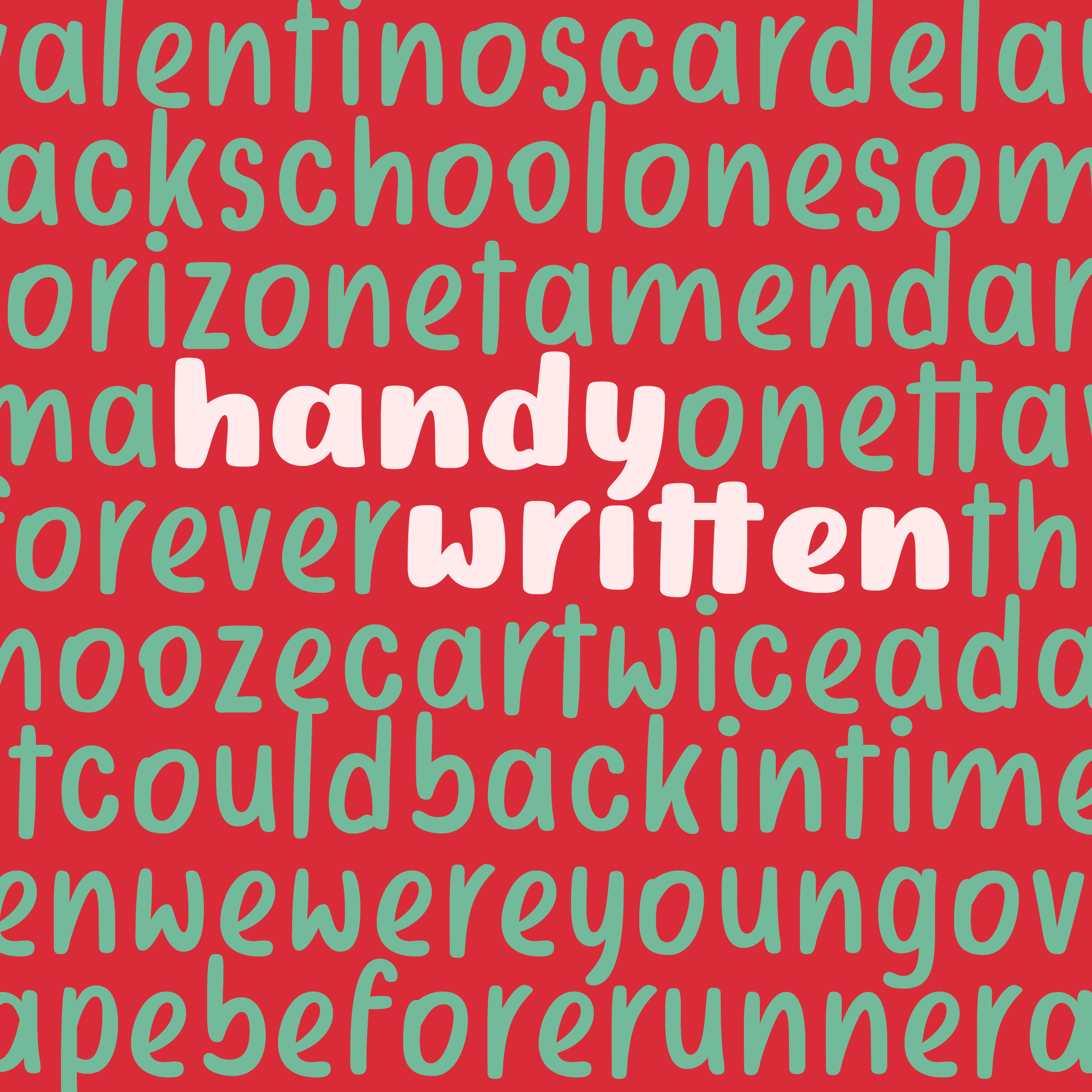
แฮนดี้ริทเทิ่น | HANDYWRITTEN
REMAKE PROJECT II
รีเมคใหม่หมด
ภาคต่อของฟอนต์ handywrite
ใช้วิธีทำงานแบบเดิม
เริ่มงานด้วย wacom แล้วค่อยมาแต่งหน้าทาปากเพิ่มหน่อยนึง
บุคลิกจะไม่ได้อิสระเสรีมากมายเหมือนแฮนดี้ไรท์
ชื่อฟอนต์ : แฮนดี้ริทเทิ่น | HANDYWRITTEN
แฮนดี้ริทเทิ่น | HANDYWRITTEN
REMAKE PROJECT II จากฟอนต์สุดฮิต ฟอนต์ "แฮนดี้ไรท์"
พัฒนาขึ้นใหม่ อัพเดต และอัพเกรดความสามารถแบบก้าวกระโดด
ยังคงความน่ารัก ใช้งานง่าย เป็นกันเอง เหมือนเดิม
เพิ่มเติมด้วยการขยายขอบเขตการใช้งานออกไป
รองรับการใช้งานได้หลากหลายภาษา
ไม่ว่าจะเป็นภาษาไทย ภาษาอังกฤษ
รวมทั้งภาษาภาคพื้นยุโรปอีกมากมาย
เพิ่มความพิเศษด้วย OpenType Features ต่าง ๆ
ไม่ว่าจะเป็นการจัดการสระ / วรรณยุกต์ไทย ด้วย Anchor Marking,
Ligatures, การทำ Kerning เพื่อความสวยงาม
ชุดฟอนต์ "แฮนดี้ริทเทิ่น"
ประกอบด้วยฟอนต์ 4 น้ำหนัก 4 ฟอนต์
• HANDYWRITTEN REGULAR / MEDIUM / BOLD / BLACK